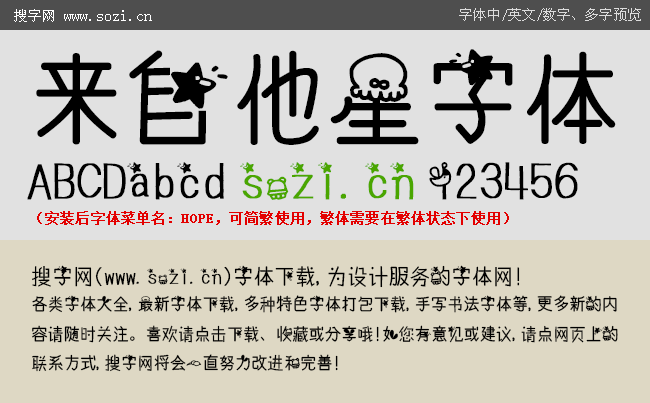
來自他星字體
搜字網(wǎng)給大家提供一款花節(jié)體字體手機(jī)中文字體下載。這款手機(jī)字體是以圓體字體為原形,將一些筆畫進(jìn)行了變形修改,筆畫間還嵌入了大量可愛的卡通圖案。使字體在具有平滑的圓體風(fēng)格的同時,又兼具兒童卡通風(fēng)格,喜歡的朋友安裝一下吧。